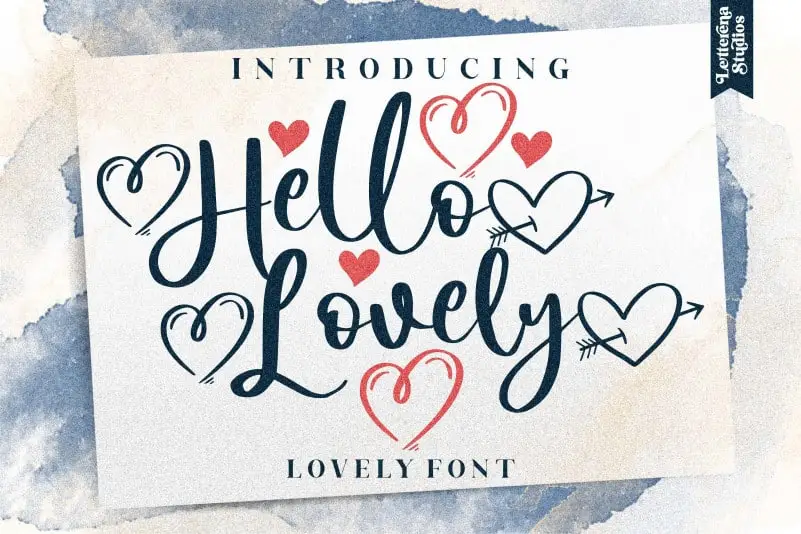
Hello Lovely Script Font – Download Grátis
A ‘Hello Lovely Script Font’ é uma elegante e fluente tipografia escrita à mão. Ela possui suíte PUA para que você possa acessar todos os gílios e swashes sem nenhum problema. Mantém seus influências de calligrafia clássicas ao mesmo tempo em que se sente contemporânea e atual. Abrace este font, transformando suas projetos em alturas ainda maiores! Esta elegante escrita à mão é ideal para designers buscando uma personalidade única e sofisticada para seus trabalhos. Com a ‘Hello Lovely Script Font’ de Designer letterenastudios, você encontra perfeição no design do seu próximo projeto.